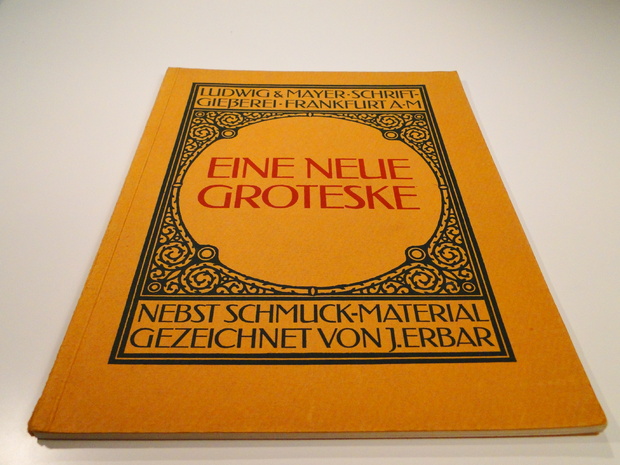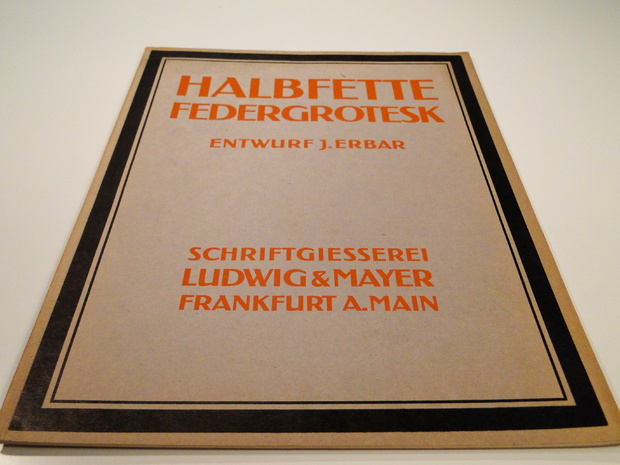
Feder Grotesk Specimen-Blätter
ich arbeite gerade an einem Revival der Feder Grotesk von Jakob Erbar, es stehen mir aber nur die Specimen-Hefte von Ludwig & Mayer aus den Jahren 1911, 1915 und 1916 (veröffentlicht in Type. A Visual History of Typefaces & Graphic Styles, Vol.2) zur Verfügung. Ich wollte Euch fragen, ob Ihr wisst, wo man weitere Musterblätter (oder auch vielleicht Material das mit Feder Grotesk gedruckt wurde) finden könnte.
ich kann auch nur mit diesen beiden mustern dienen:
auf die schnelle habe ich nur das obere von 1911 in dem buch von jan tholenaar gefunden.
falls dir das andere was nützt, könnte ich dir ggf. ein paar seiten scannen.
übigens interessantes versal-ß:
auf die schnelle habe ich nur das obere von 1911 in dem buch von jan tholenaar gefunden.
falls dir das andere was nützt, könnte ich dir ggf. ein paar seiten scannen.
Ich hätte die Broschüre "Alphabete und Schmuck für typographische Entwürfe"
mit Alphabeten der Feder Grotesk, Feder Grotesk halbfett und Feder Grotesk Initialen als PDF.
Stammt aus der Zeit 1914/15.